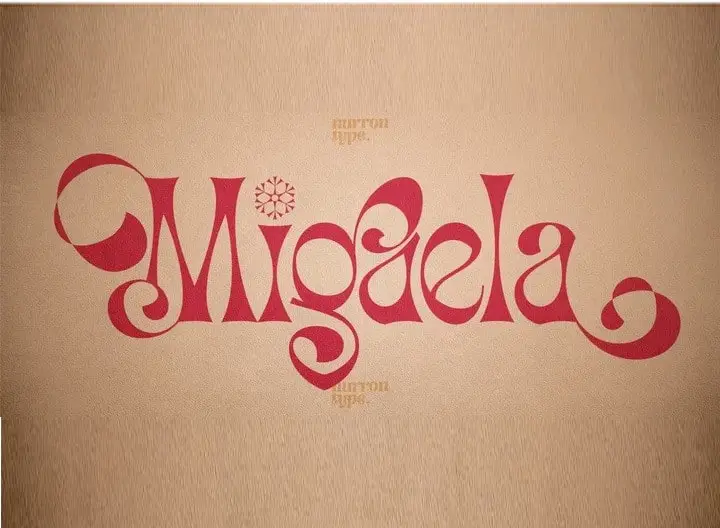
Introduzimos a Migaela Display Font, uma nova face tipo para exibição. Criada pelo font designer Nurrontype, essa face é uma oferta fresca que incorpora um ar descontraído e divertido perfeitamente adaptado às aplicações como capas de livros em quadrinhos, personagens de desenhos animados, ou temas infantis. Perfeito para ilustrar as histórias coloridas dos seus projetos, esta face tipo é o elemento ideal que enriquece os elementos visuais. Não perca a oportunidade de dar vida às suas ideias com um toque de diversão e criatividade.